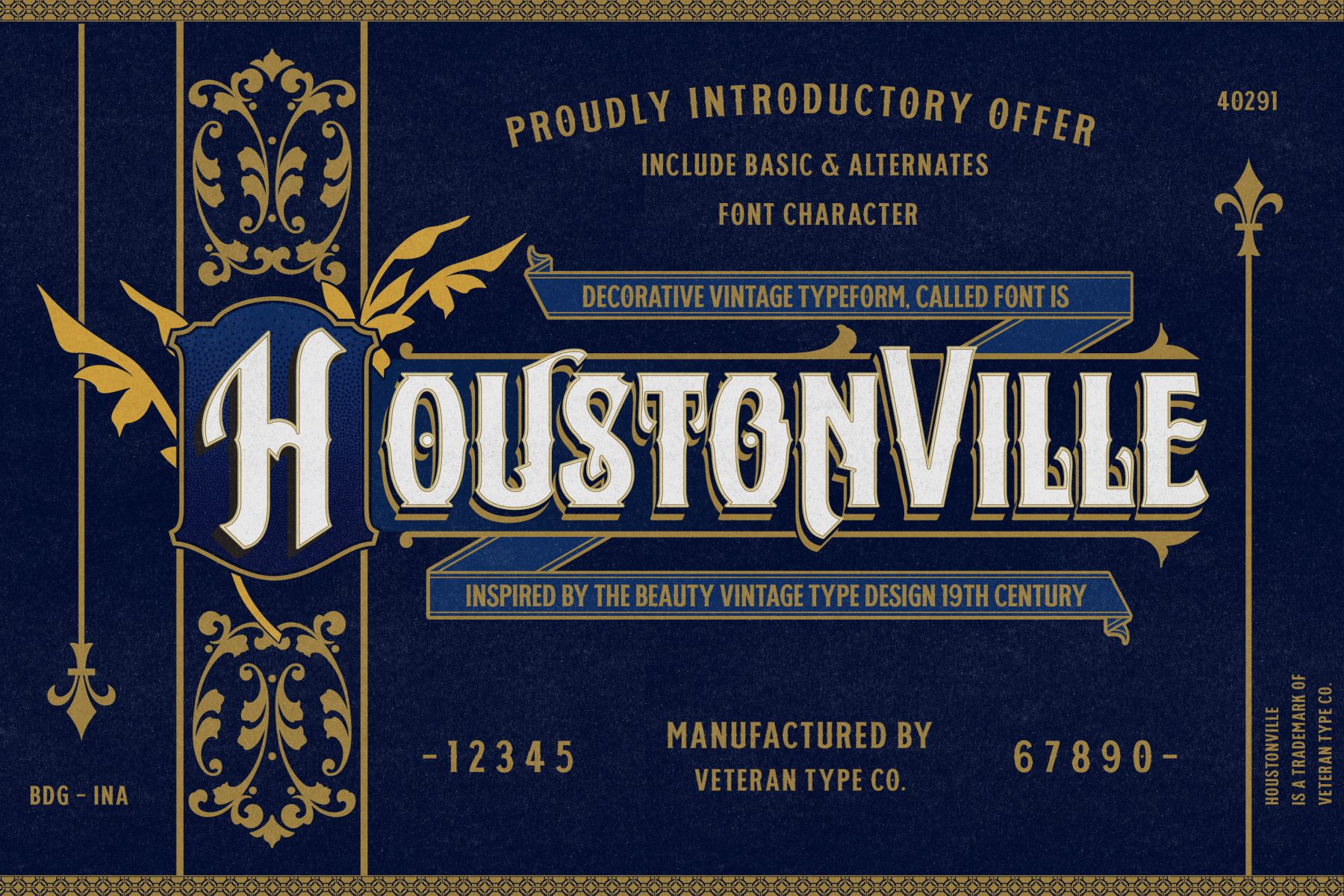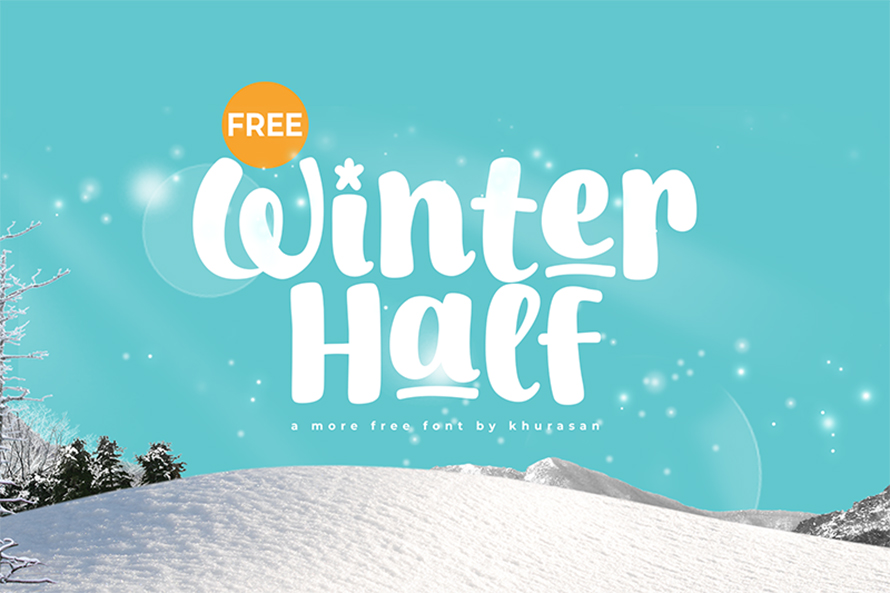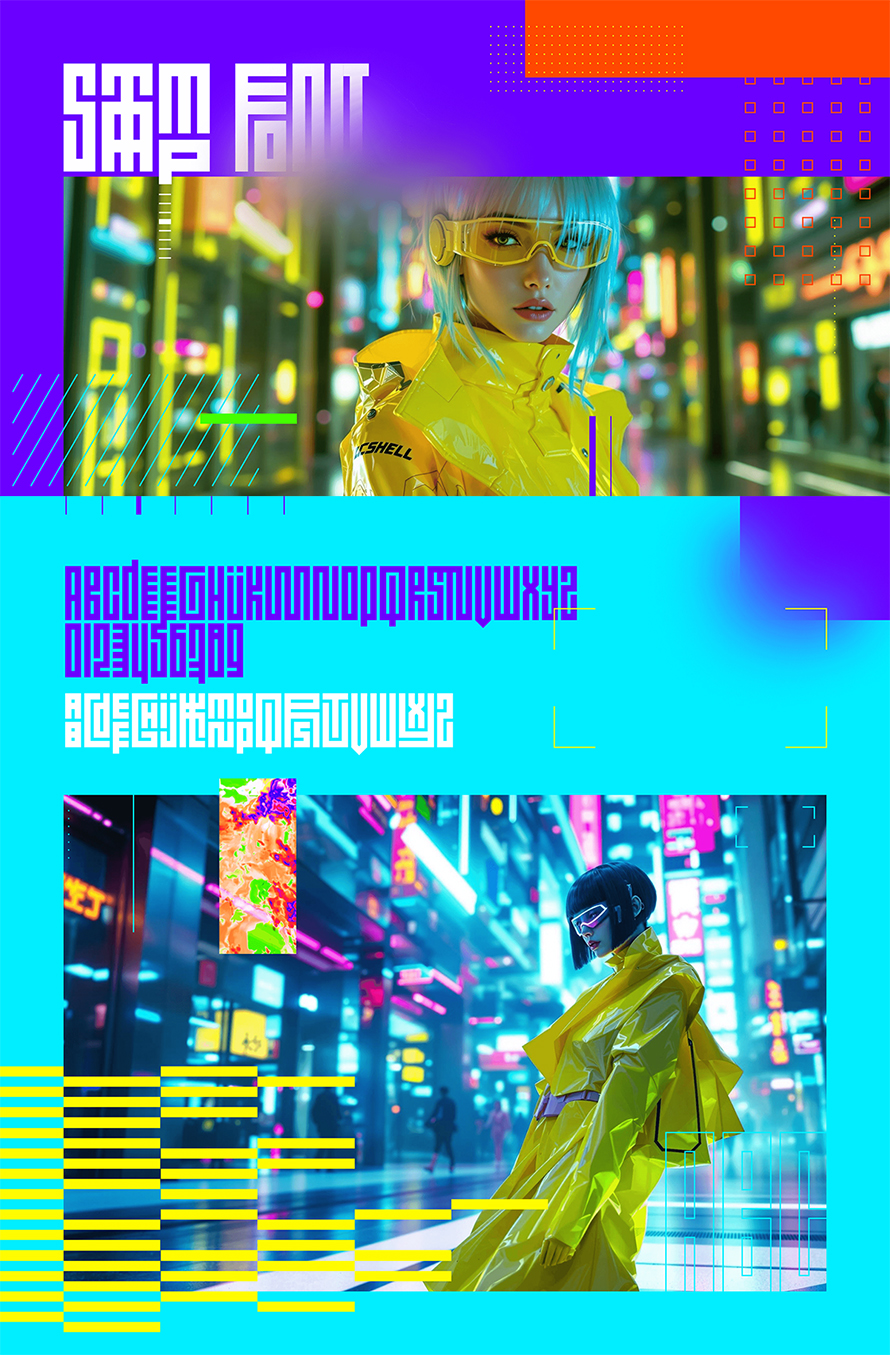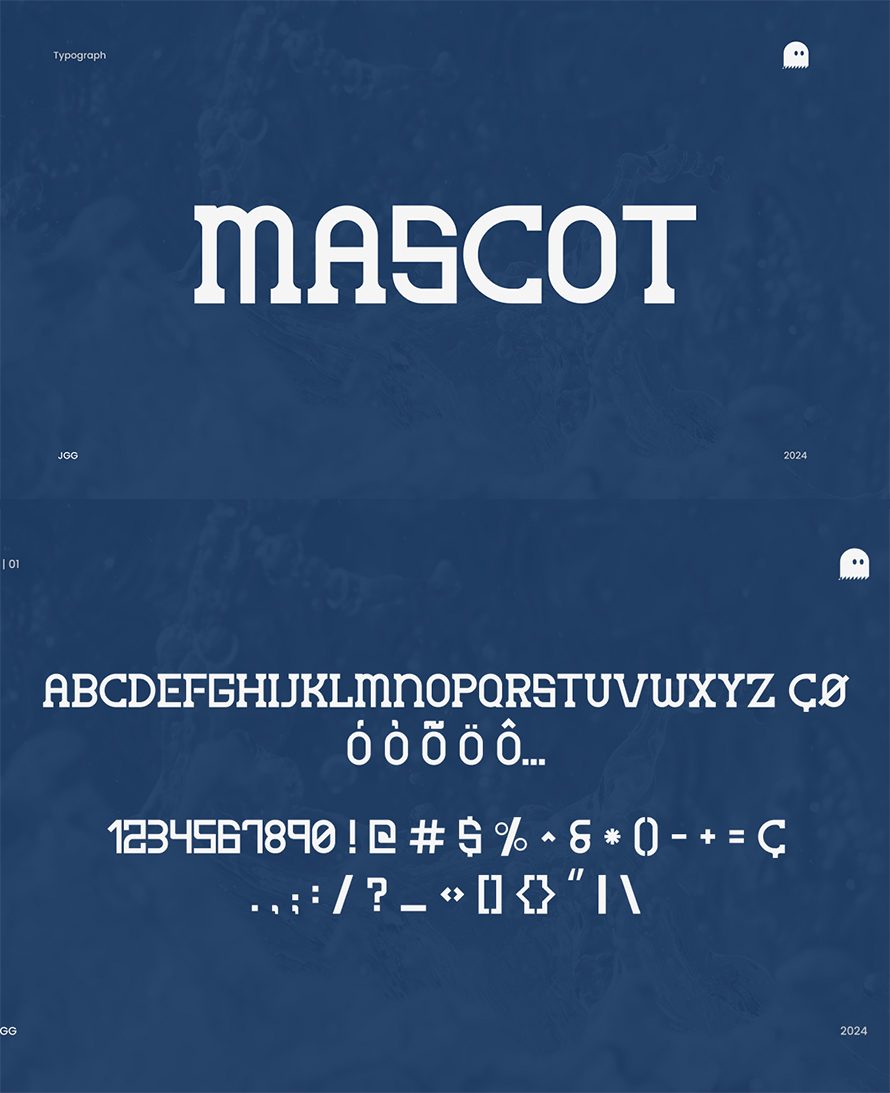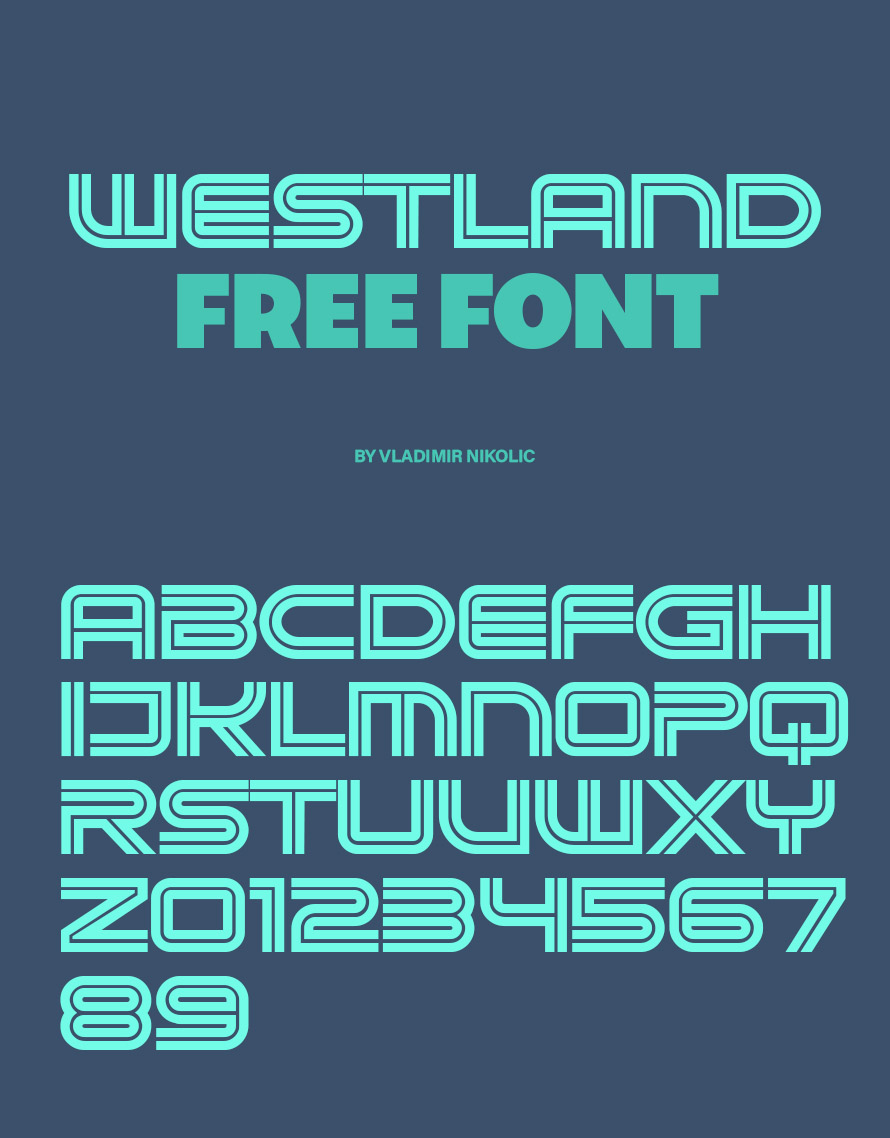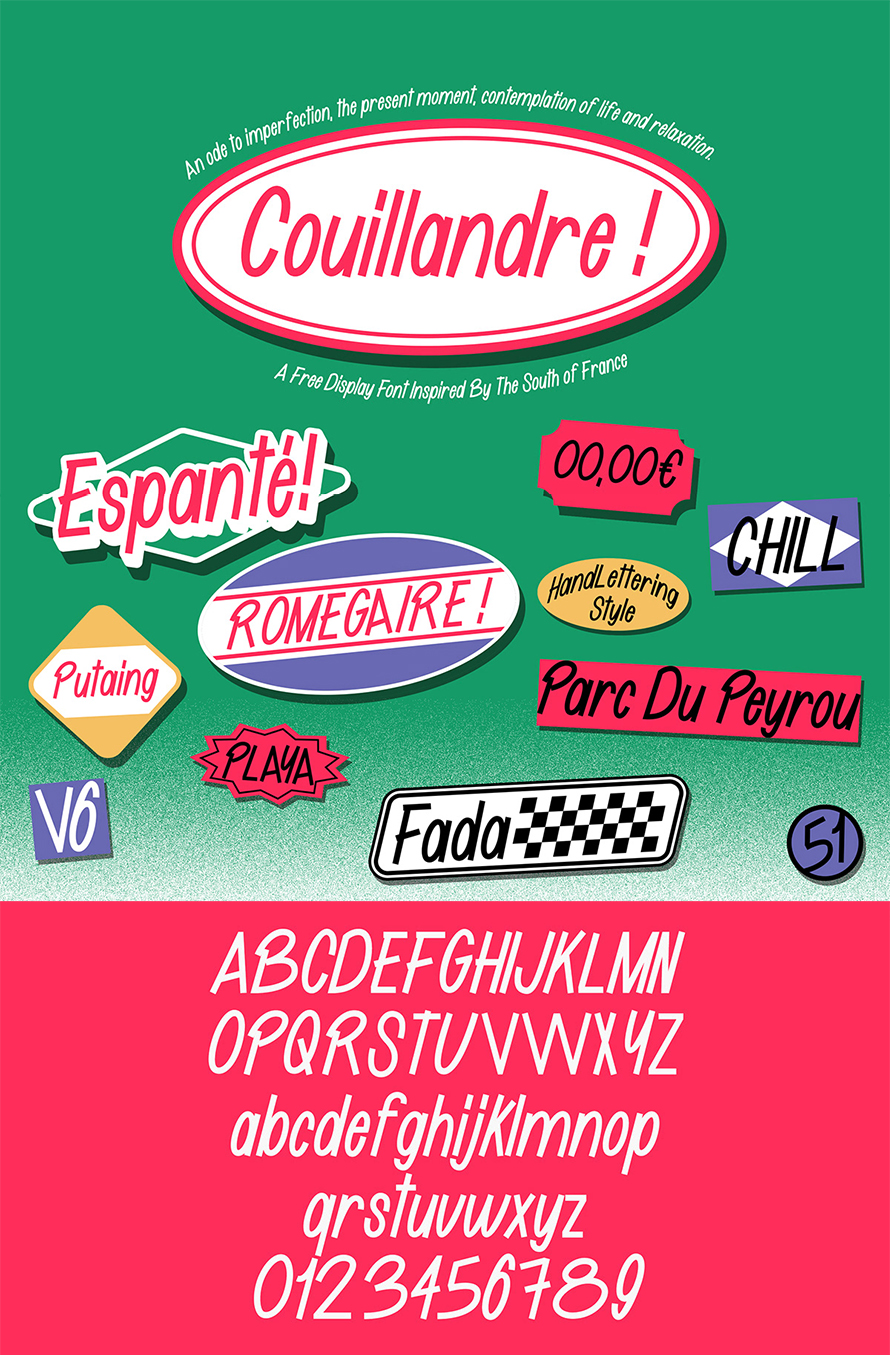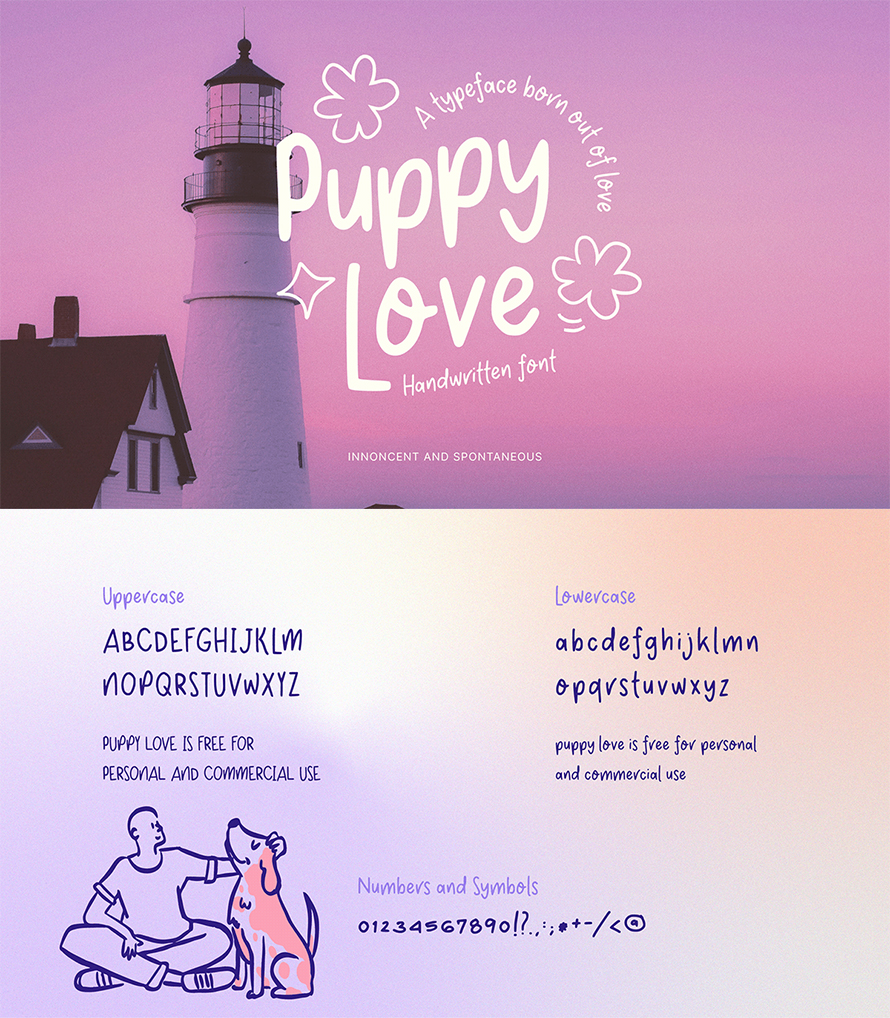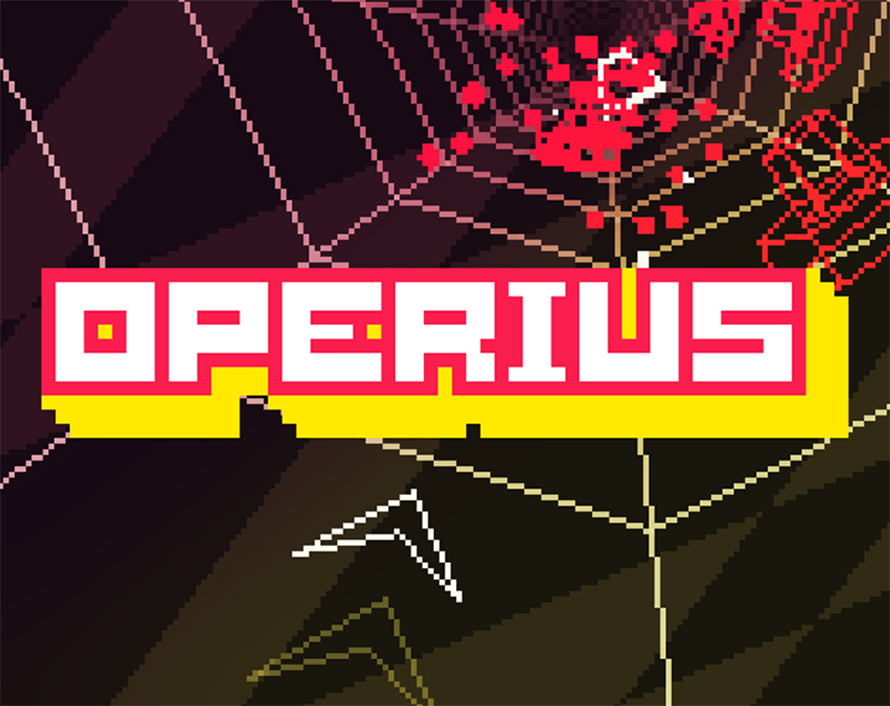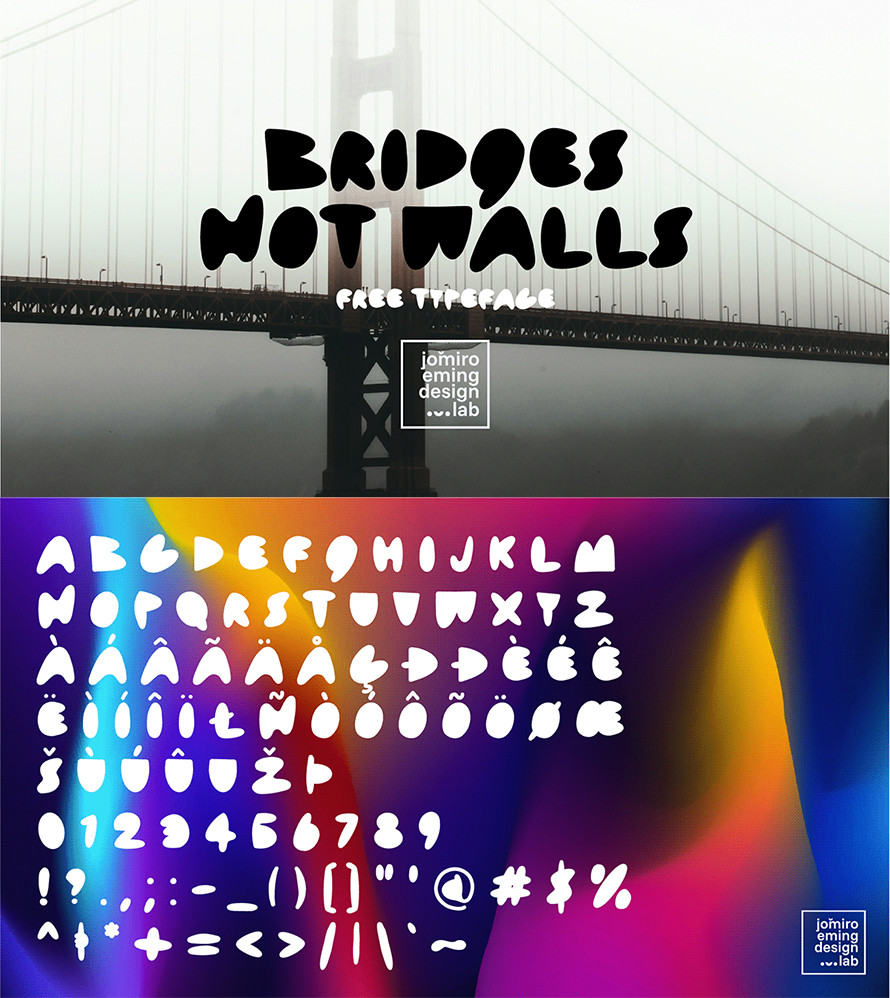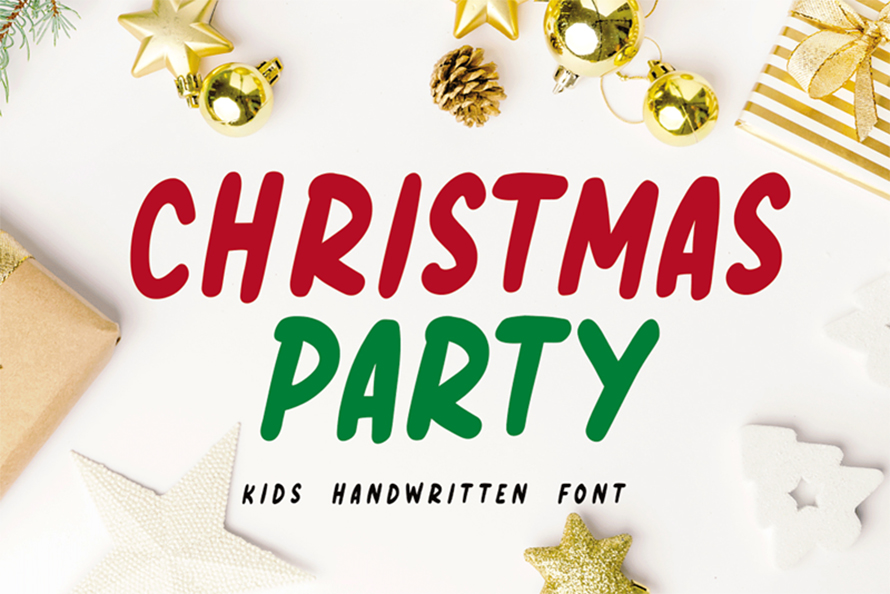
New Free Fonts For Graphic Design
25+ Free Fonts for Grafik Designer
Im Design sind Schriftarten entscheidend, um großartige visuelle Effekte zu erzielen. Für Grafikdesigner kann die richtige Schriftart ein einfaches Projekt in etwas Beeindruckendes verwandeln. Wenn Sie Inspiration benötigen, haben wir über 25 neue kostenlose Schriftarten, die Ihnen helfen können, Ihre Arbeit zu verbessern.
Die Kraft der Schriftarten im modernen Design
Typografie ist mehr als nur die Anordnung von Buchstaben; es geht darum, Emotionen zu wecken und Botschaften effektiv zu vermitteln. Egal, ob Sie eine mutige Werbekampagne gestalten, eine elegante Website entwerfen oder ein unvergessliches Logo erstellen, Schriftarten sind das Fundament Ihres Designs. Deshalb ist es für jeden Designer entscheidend, über die neuesten Schriftart-Trends auf dem Laufenden zu bleiben.
Kostenlose Schriftarten sind ein Segen für Grafikdesigner, insbesondere für diejenigen, die mit knappen Budgets oder freiberuflichen Projekten arbeiten. Sie bieten eine kostengünstige Möglichkeit, verschiedene Stile zu erkunden, ohne dabei Kompromisse bei der Qualität einzugehen. Die zunehmende Verfügbarkeit von Plattformen für kostenlose Schriftarten hat den Zugang zu hochwertigen Schriftarten für den professionellen Gebrauch einfacher denn je gemacht. Von sauberen Sans-Serifs bis hin zu verspielten Display-Schriftarten – diese kostenlosen Optionen decken jeden kreativen Bedarf ab.
Jazzy Rabbit Schriftart
Die Jazzy Rabbit Schriftart ist eine verspielte, ausdrucksstarke Schriftart, die die Essenz von Spaß und Energie einfängt. Mit fetten, geschwungenen Buchstaben vereint sie einen Retro-Charme mit modernem Flair. Perfekt für Überschriften, Poster und Branding, verleiht diese Schriftart jedem Design eine verspielte Note, ohne dabei Lesbarkeit und Stil zu vernachlässigen.
Houstonville Schriftart
Die Houstonville Schriftart ist eine elegante, moderne Serifenschriftart, die Eleganz mit Lesbarkeit verbindet. Ihre scharfen Linien und verfeinerten Kurven machen sie ideal für professionelles Branding, redaktionelle Designs und anspruchsvolle Druckprojekte. Die Schriftart strahlt einen zeitlosen, klassischen Charme aus und verleiht jedem Design eine Note von Luxus und Klasse.
Westland Schriftart
Die Westland Schriftart ist eine stilvolle, zweizeilige Schriftart, die moderne Ästhetik mit geometrischer Präzision verbindet. Mit scharfen, sauberen Linien und einem einzigartigen Schichtdesign verleiht sie Überschriften und Logos Tiefe und visuelles Interesse. Ihr zeitgenössischer Charme macht sie ideal für kreative Projekte, die eine mutige, auffällige Schriftart erfordern.
Mascot Kostenlose Schriftart
Mascot ist eine Serifenschriftart, die klassische Eleganz mit einem modernen Touch verbindet und sich perfekt eignet, um Stil und Charakter zu vermitteln. Ihr Design zeichnet sich durch verfeinerte Formen und scharfe Linien aus, die eine Balance zwischen Tradition und zeitgenössischer Ästhetik schaffen. Ideal für Überschriften, Logos und Druckmaterialien strahlt Mascot Autorität und Stil aus, ohne dabei die Lesbarkeit zu beeinträchtigen. Ihr Charme ist unbestreitbar, was sie zur perfekten Wahl für die Schaffung einer mutigen und unvergesslichen visuellen Identität macht.
Stamp Schriftart
Dies ist Stamp – eine variable Schriftart, die von chinesischen Siegeln inspiriert ist. Mit 471 Ligaturen können Sie leicht interessante Muster aus jedem Wort, Satz oder Absatz erstellen. Unterstützt werden grundlegende lateinische Zeichen, Zahlen und einfache Symbole.
Dbacks Schriftart
Schriftarten erzählen Geschichten und verwandeln Worte in Kunst. Eine kostenlose Schriftart zu finden, fühlt sich an wie ein Schatzfund, der kreative Türen ohne Kosten öffnet. Von schlanken modernen Linien bis hin zu verspielten Kurven – kostenlose Schriftarten ermächtigen Designer, Schriftsteller und Träumer. Sie bieten grenzenlose Ausdrucksmöglichkeiten und beweisen, dass Kunst nicht vom Preis abhängt, sondern von der Vorstellungskraft, die frei mit der Welt geteilt wird.
Couillandre Kostenlose Schriftart
Schriftarten, die stillen Verbündeten der Designer, bringen Ideen zum Leben. Kostenlose Schriftarten, zugängliche Schätze, ermöglichen Kreativität ohne Kosten. Von eleganten Serifen bis hin zu mutigen Sans-Serifs verwandeln sie einfache Worte in kunstvolle Aussagen. Jede Schriftart erzählt ihre eigene Geschichte und lädt Nutzer ein, zu erkunden, anzupassen und auszudrücken, wodurch einfacher Text zu einem Meisterwerk des Stils wird.
Puppy Love Kostenlose Schriftart
Puppy Love ist ein spontaner Akt der Unschuld, der meinen Traum erfüllt. Ich habe schon immer geliebt, wie eine Schriftart einem Design einen starken Charakter verleihen kann. Die Erstellung meiner eigenen Schriftart war schon lange ein Traum von mir. Also sagte ich mir, dass, wenn ich jemals meine eigene Schriftart entwerfen würde, sie etwas ganz Besonderes sein sollte, das ein wenig von meiner Persönlichkeit widerspiegelt.